En voilà un titre qu’il est long ! Je n’en ai pourtant pas trouvé de meilleur pour décrire ce qui va suivre : un travail d’illustration et de typographie mettant en scène différents types d’activités économiques et de commerces, le tout d’une bien curieuse façon.
Jing Zhang est une illustratrice chinoise basée à l’est de Londres, un quartier réputé, paraît-il, pour être un aimant à hipsters, mais surtout un pôle d’attractivité pour les créatifs en tout genre.
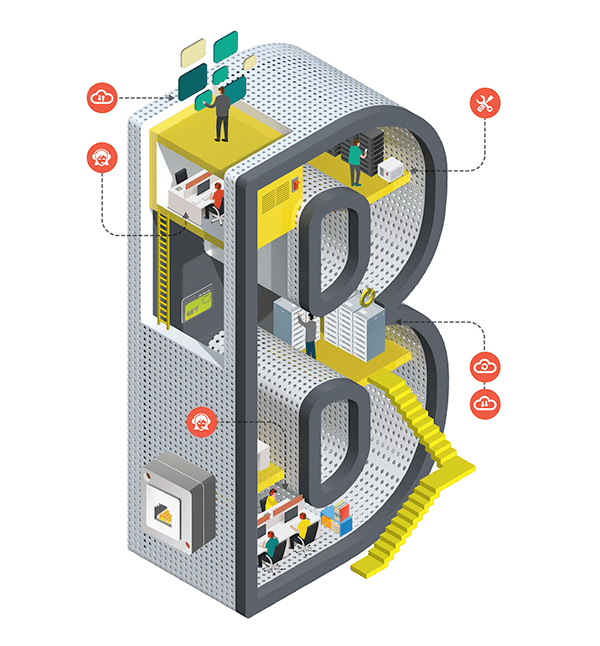
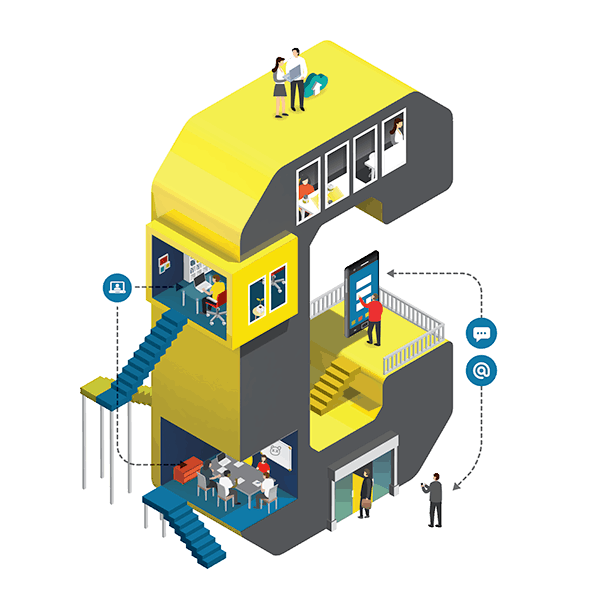
Grâce à son talent et à son style unique, Jing Zhang travaille avec une clientèle allant de l’industrie à l’édition en passant par la publicité, l’automobile ou même les compagnies aériennes, et ce depuis 7 ans.
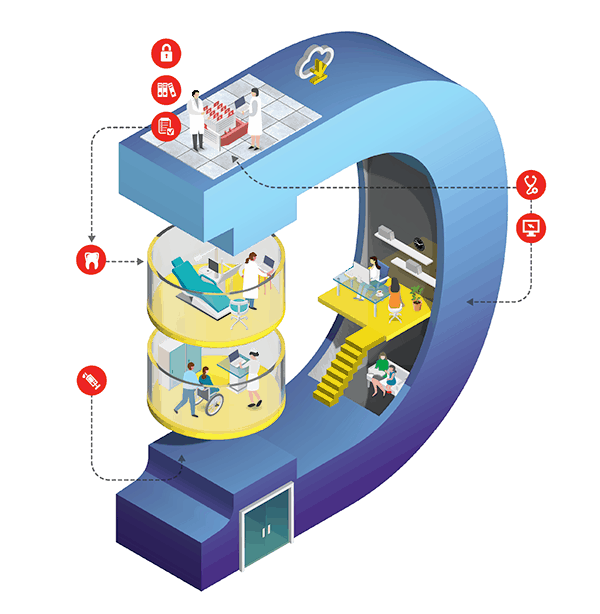
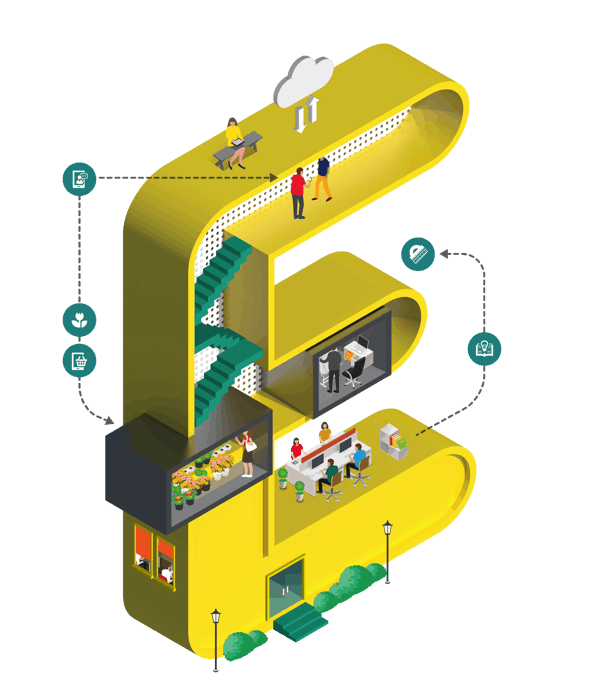
La rencontre entre la typographie et l’architecture n’est pas quelque chose de nouveau, mais le travail de Jing Zhang a le mérite de sortir du lot. Au-delà de simples lettres mises en volume et illustrées, chacune d’entre elles raconte une histoire et tourne autour d’une activité économique ou d’un ensemble d’activités.
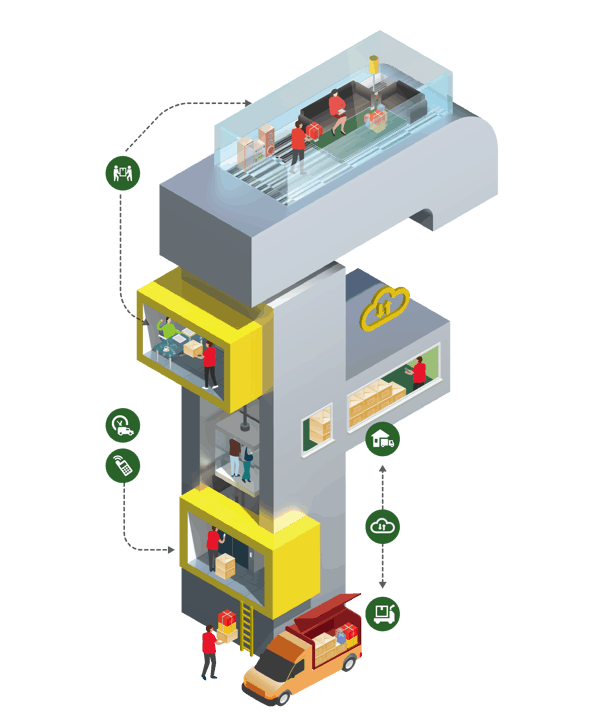
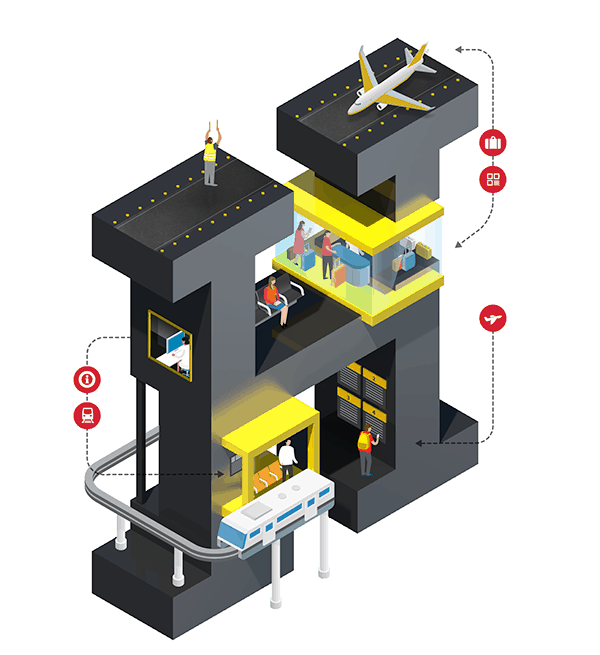
La lettre « I », par exemple, nous présente le processus et le chemin par lequel passent nos légumes depuis la ferme jusqu’à nos assiettes. Chaque lettre est ainsi bourrée de détails qui lui donnent vie.
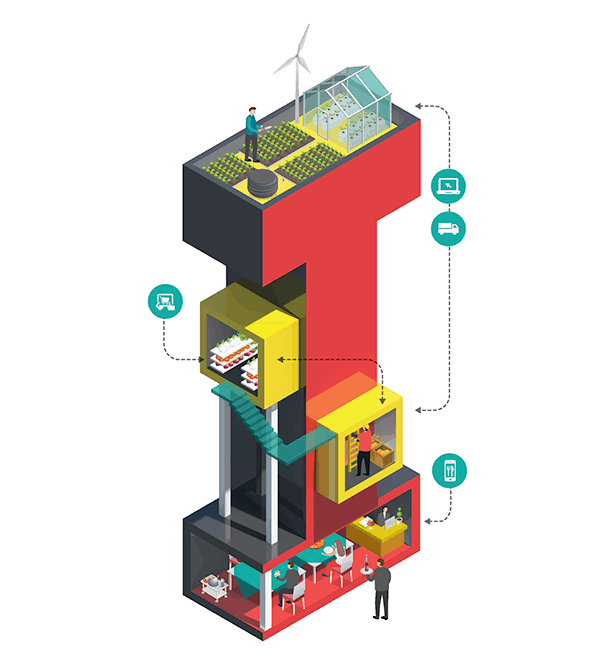
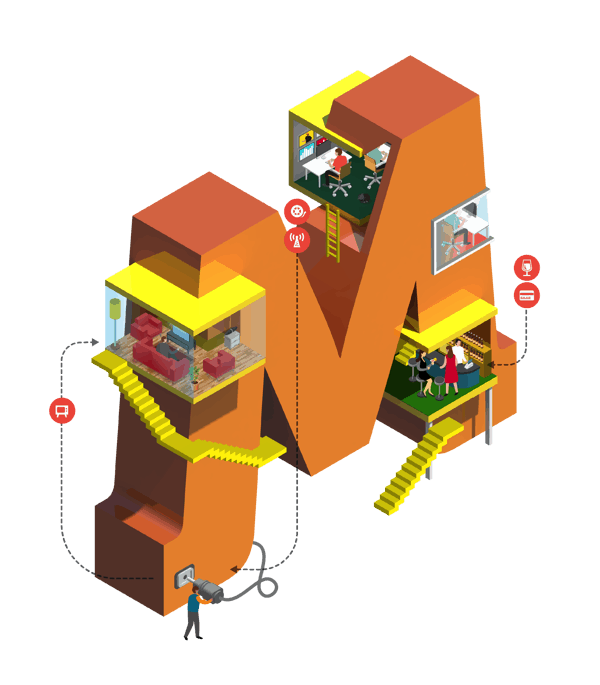
« Le groupe Sprint dispose d’une très large gamme de produits et de prestations. L’objectif était de créer une apparence cohérente et une image qui vende le panorama des offres de Sprint comme une seule et même entité, capable de beaucoup de choses différentes et faisant appel à de nombreux types d’entreprises différents. Les visuels devaient être fluides, intelligents, techniques, innovants et raffinés. »